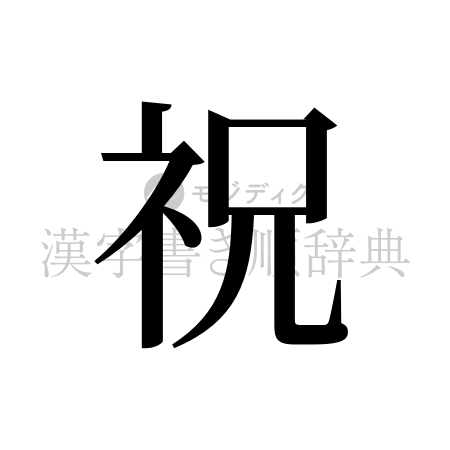
「祝」の意味
- 祝いの意を表す。
- 神に祈る、祭る。
- 祝福する、喜びを表す。
- 祝儀、祝い事。
- 神職に関すること。
漢字は1文字で多様な意味を持ちますが、「祝」を英語で表す場合、一般的には celebrate, congratulate などがあります。
「祝」の成り立ち・由来
| 構造 | 示(祭壇・神)+兄(口を開いて祈る人) |
「示」と「兄」を組み合わせた会意文字です。「示」は神を祭る祭壇をかたどり、神事に関わることを表します。「兄」は大きな口をもつ人を横から見た形で、祭壇の前でひざまずき、口を開いて神に祈りの言葉を唱える人を示します。両者を合わせて、神に祝詞(のりと)を告げる人、すなわち神への祈りを表し、そこから「いわう」「祝福する」の意味が生まれました。なお「兄」を音符と見て会意兼形声とする説もあります。旧字体では「示」を用い、現在は「礻(しめすへん)」の形に整えられています。
※ 「兄」を音符と捉え会意兼形声とする説もあります。
- 祝典 - しゅくてん
- 祝いの式。祝賀の式典。
- 奉祝 - ほうしゅく
- つつしんで祝うこと。奉賀。
「祝」は名前に使える漢字です。